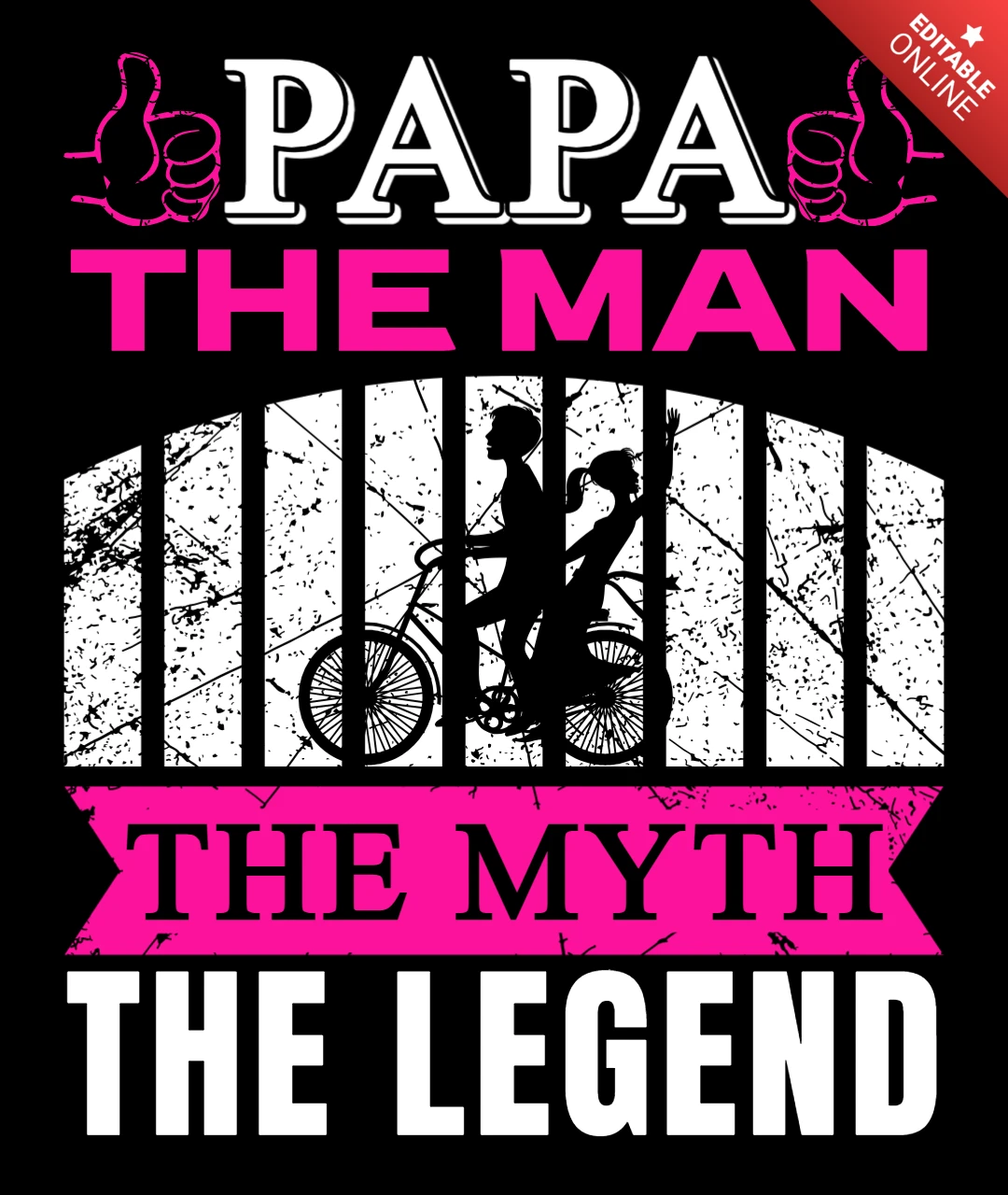
Modèle de typographie vintage : "papa l'homme, le mythe, la légende"
Éditer dans Design Studio Télécharger en JPGLibérez votre créativité grâce à nos modèles typographiques audacieux et vintage ! Parfaits pour les t-shirts, les affiches et les vêtements, ils comportent des citations humoristiques telles que "papa, l'homme, le mythe, la légende".
Modèle de conception typographique audacieuse : célébrer "papa, l'homme, le mythe, la légende"